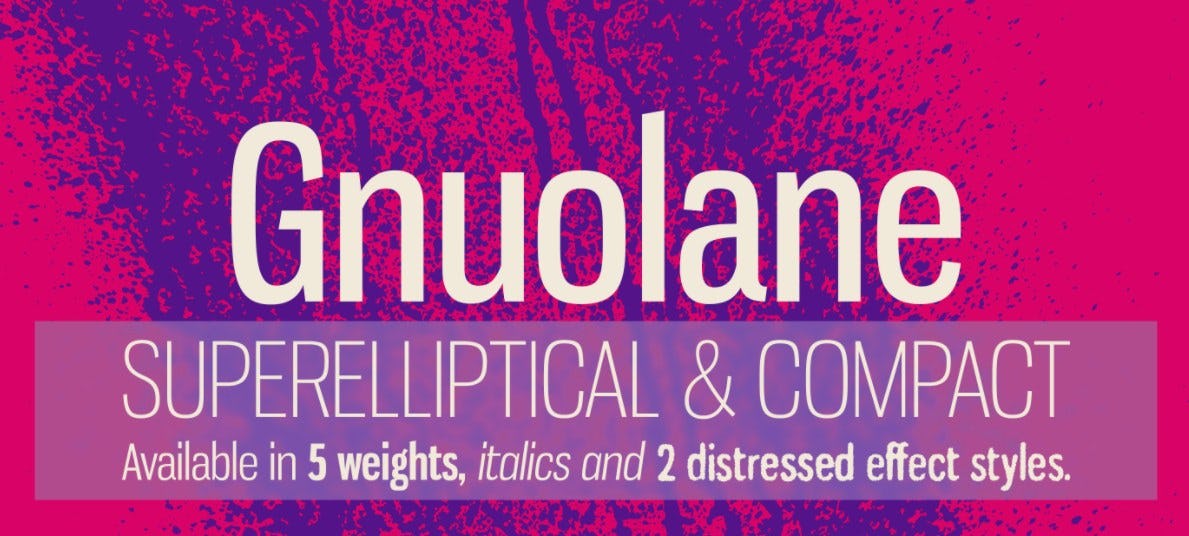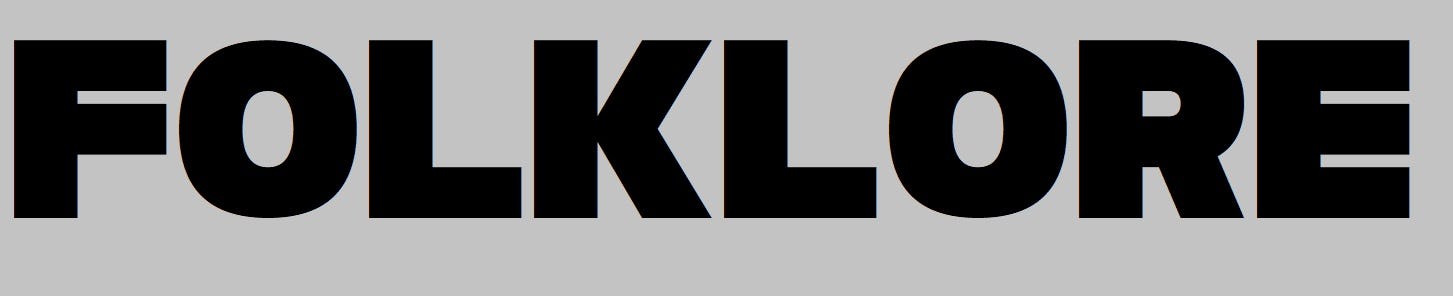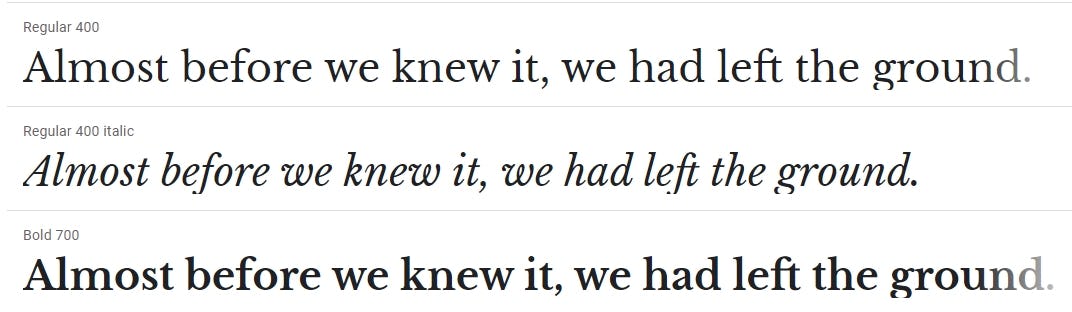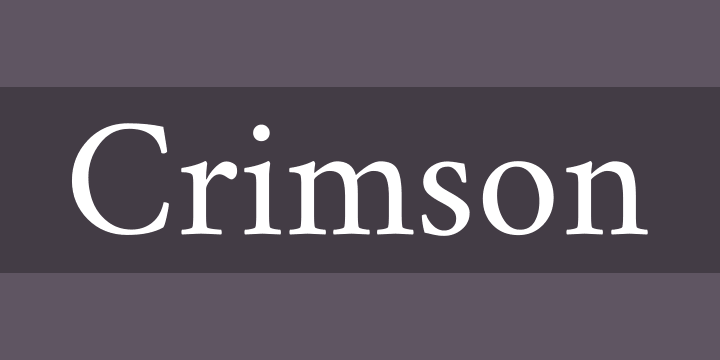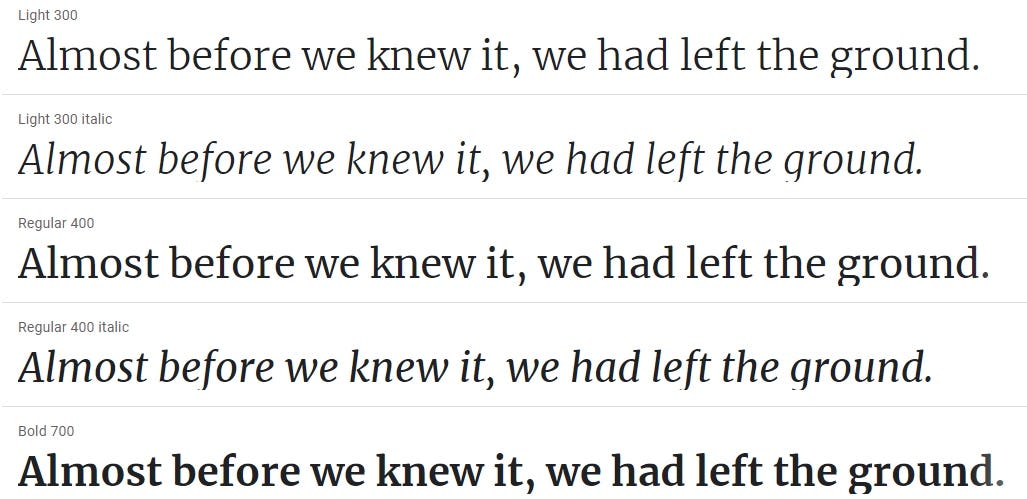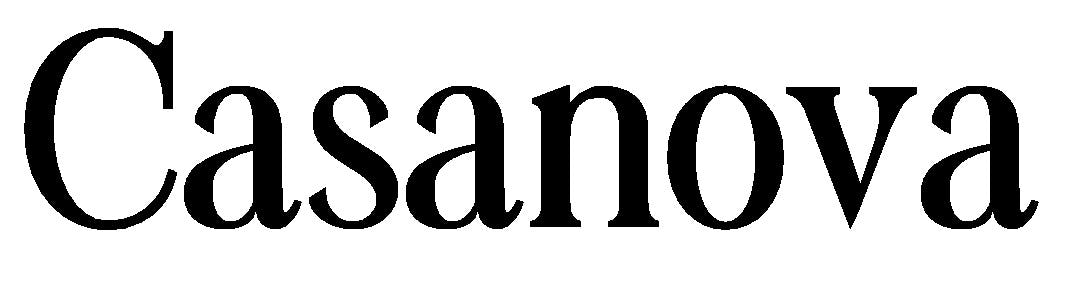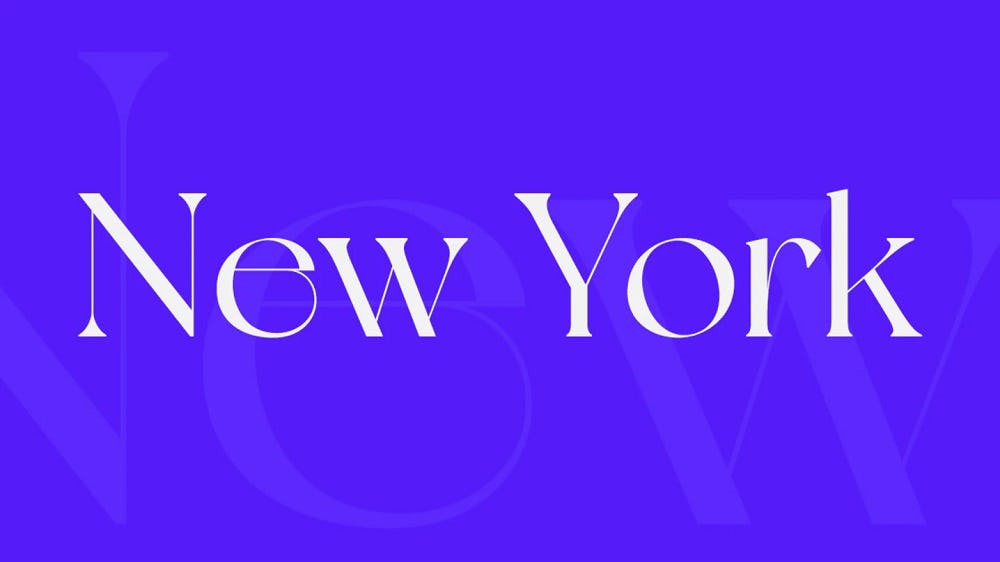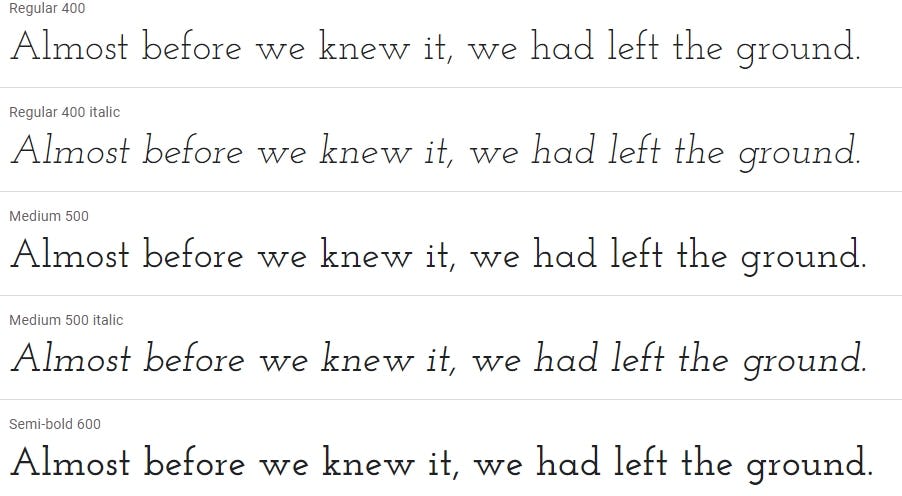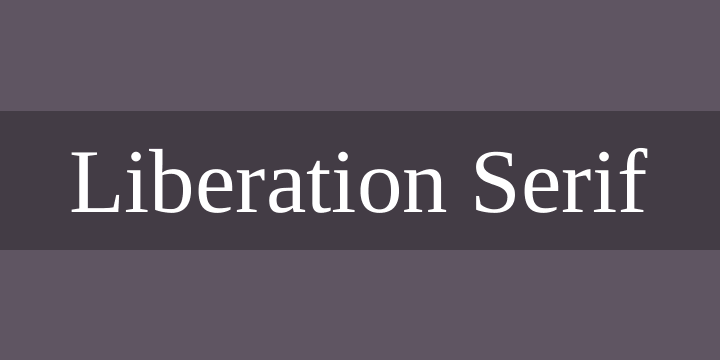
¿Has pensado alguna vez lo importantes que son las tipografías para revistas? Si te pones a analizar, seguramente recuerdes cuál es, por ejemplo, la tipografía de Vogue, o la de Rolling Stones. Y es que la fuente es un aspecto súper importante de la identidad de marca de una publicación.
Las revistas son un medio de comunicación en el que prima la parte gráfica por encima de todo. Siempre nos llama la atención el diseño de la portada o la maquetación del contenido, ¿pero qué sería de todo este diseño sin letras?
Por eso, en este artículo aprenderás sobre la importancia de las tipografías para revistas y, como bonus track, te dejamos algunas fuentes que podrás descargar gratis (especialmente en caso de que estés pensando en cómo hacer una revista digital sobre lo que te apasiona).
Si deseas conocer un poco más sobre la importancia de las letras de revistas y descargar las mejores tipografías para revistas, ¡acompáñanos!
Todo sobre el diseño editorial
¿Qué es el diseño editorial? Para seleccionar las mejores tipografías para revistas, primero es necesario entender de qué trata el diseño editorial. El diseño editorial es una rama del diseño gráfico que se encarga de crear todo tipo de publicaciones que van desde revistas y periódicos hasta libros.
Pero la persona indicada para definir lo que es el diseño editorial es Rosa Rodríguez, nuestra profesora del curso online Adobe InDesign: Diseño editorial desde cero.
"El diseño editorial es una disciplina que tiene el objetivo de generar publicaciones entendibles, legibles y atractivas para el lector. Para hacer esto posible, se debe combinar la sensibilidad artística y la destreza técnica".
Por más cliché que suene, todo entra por los ojos y el diseño editorial no es la excepción. Supongamos que estás en una librería y ves tres revistas que tratan un mismo tema en la portada. Estamos seguros que te inclinarás por la que más te jaló la vista. Esa es, precisamente, la labor del diseño editorial: diferenciarse del resto y que podamos adquirir la publicación.
Para lograr su cometido, el diseño editorial tiene seis elementos clave:
Flat plan: es el boceto en el que distribuirás el contenido en la publicación.
Formato: definir el formato de la publicación te permitirá establecer la distribución de los contenidos en la página.
Retícula: estructura invisible que el diseñador construye para ordenar los contenidos en las páginas y crear uniformidad.
Color: te ayuda a destacar partes del texto, a diferenciar secciones o capítulos, así como a darle una identidad a la revista.
Cubierta: elemento de atracción que se crea para que el lector pueda adquirir tu publicación.
Tipografía: a este punto queríamos llegar. La tipografía es la clave para jerarquizar el contenido. Te ayudará a saber (como lector) qué es un titular, un destacado, pie de foto, una cita, entre otros.
Entonces, basándonos en este concepto general del diseño editorial, ¿en qué debes basarte para elegir las correctas tipografías para revistas? ¡Vamos al siguiente punto!
Tips para elegir tipografías para revistas
¿Sabías que una correcta elección de las tipografías para revistas puede influir notablemente en el carácter y personalidad de tu publicación?
Sucede que las revistas muestran el mayor número de elementos de contenido a diferencia de otro tipo de publicación, como un libro o periódico, por ejemplo. Si bien cada página debe ser diferente, el conjunto debe estar marcado por una personalidad bien definida.
Por ese motivo, es sumamente importante saber elegir las tipografías para revistas correctas y, sobre todo, encontrar el contraste perfecto para las páginas. A continuación, unos tips para elegir las tipografías ideales para revistas.
Legibilidad: las tipografías para revistas que suelen utilizarse pertenecen a las familias Serif y Sans Serif debido a su alto grado de legibilidad.
Tipo de contenido: deberás elegir alguno de los tipos de tipografías que consideres acorde al contenido que vayas a publicar. Recuerda que lo que necesitas es transmitir algo.
¿Impresa o digital?: ten en cuenta que existen tipografías especialmente diseñadas para la impresión. Si se trata de una revista digital, también tienes que considerar que la fuente para impresión podría no ser la más adecuada.
Tamaños de tipografía: El tamaño de la tipografía para revistas que elijas es muy importante para determinar la jerarquización del contenido. Debes diferenciar el tamaño del titular, del cuerpo de texto, de las leyendas, entre otros contenidos de tu página.
Atención con los estilos: para complementar el tamaño de la fuente de una revista debes elegir el estilo correcto (regular, cursiva, bold o condensed). Vendría bien que, por ejemplo, tu titular pueda tener el estilo condensed (perfecto para titulares por su ahorro de espacio), mientras que las citas podrían estar en cursiva.